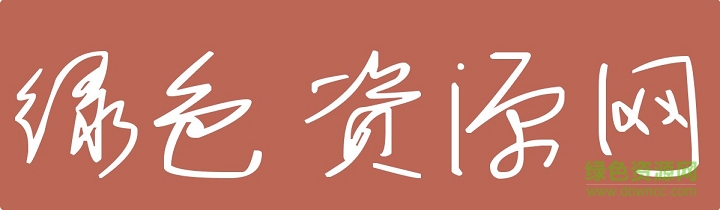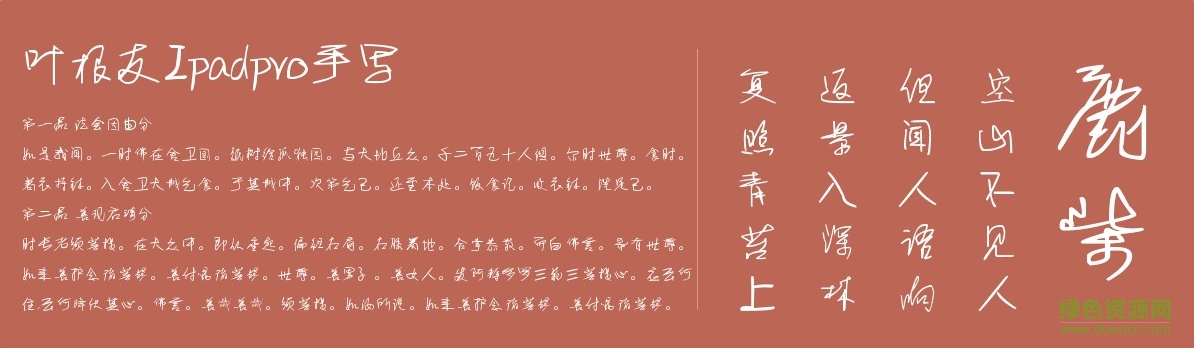
葉根友Ipadpro手寫(xiě)體是一款經(jīng)典的葉根友手寫(xiě)字體,字體纖細(xì)極具特色,使用領(lǐng)域官方,時(shí)刻彰顯個(gè)人魅力??靵?lái)綠色資源網(wǎng)下載體驗(yàn)吧!
一位從事設(shè)計(jì)創(chuàng)意的好友唐曾平先生的一句話建議,說(shuō)是否可以用ipad pro來(lái)寫(xiě)字體...于是開(kāi)始了這款字體的創(chuàng)作,這是利用ipad pro寫(xiě)字版用手指寫(xiě)的字體充分用碎片時(shí)間來(lái)書(shū)寫(xiě),候車(chē)廳、床上、辦公室都留下了她的身影讓書(shū)法與現(xiàn)代高科技的結(jié)合,指隨心動(dòng)方式來(lái)創(chuàng)作字體的感覺(jué)很好一種新型工具的一種嘗試,雖然不太好寫(xiě),經(jīng)過(guò)幾個(gè)月的努力,總算是把6763個(gè)漢字寫(xiě)好了